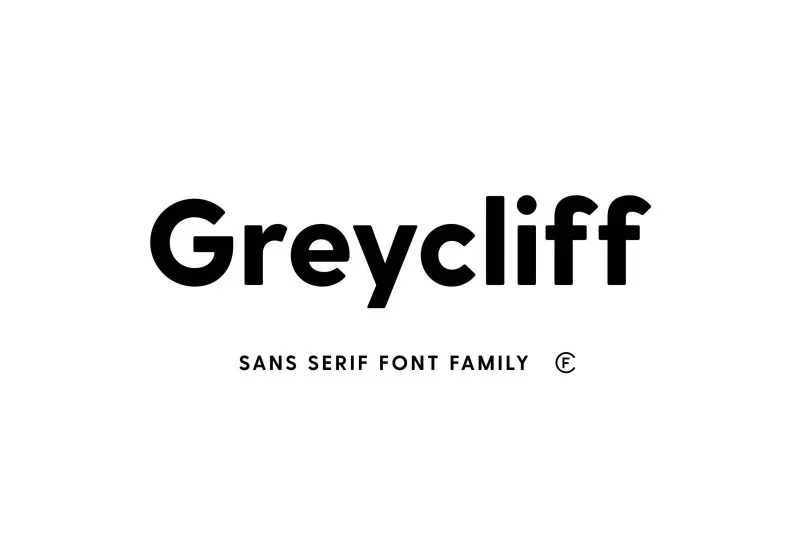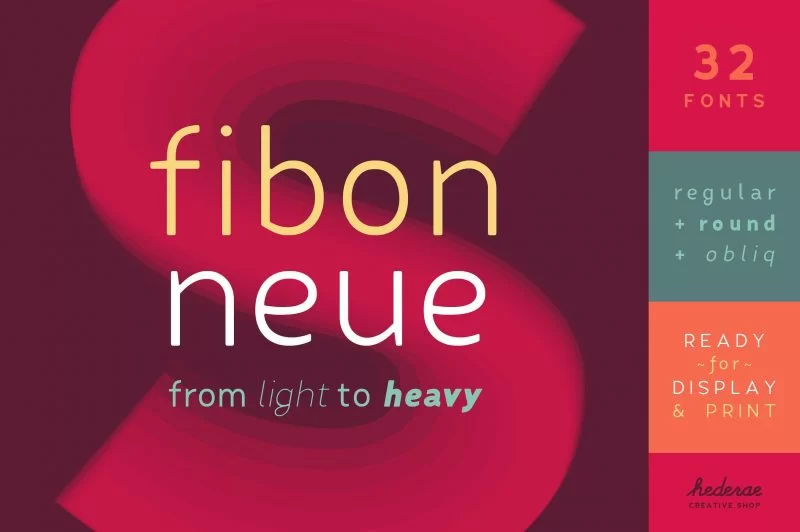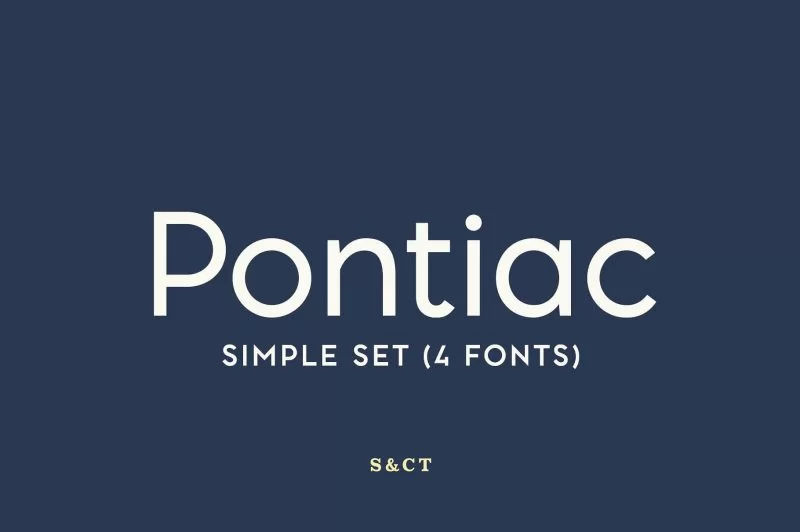
50 أفضل الخطوط للسيرة الذاتية
نشرت: 2022-06-25أفضل الخطوط على الإنترنت للسير الذاتية الإبداعية. فيما يلي قائمة شاملة بأفضل الخطوط للسيرة الذاتية لإحداث تأثير فوري.
هناك المئات من الأشياء التي يجب أن تترك السيرة الذاتية المثالية انطباعًا دائمًا ؛ الخط هو أحد أهم الخطوط على الإطلاق.
قد يكون لديك ألف خط للاختيار من بينها لإنشاء سيرتك الذاتية المثالية. ولكن لن تساعدك كل الخطوط في إنجاحها.
فيما يلي بعض من أفضل الخطوط سريعة الاستجابة التي تم إنشاؤها خصيصًا لهذا الغرض.
كاليبري
لا شك أن Calibri بتصميمها المستدير بمهارة هو أحد أفضل الخطوط لعمل السيرة الذاتية. له مظهر احترافي مع ميزات حديثة مقارنة بالخطوط الأخرى المتوفرة اليوم.
إنه الخط الافتراضي في PowerPoint و Excel و Word والعديد من المنصات البارزة الأخرى.
ستريما
هندسي بلا رقيق هو مثال نموذجي على بساطتها ووضوحها. يوفر دعمًا واسعًا للغة وميزات طباعة احترافية بالكامل.
هيلفيتيكا
إنه محرف يستخدم على نطاق واسع لأغراض السيرة الذاتية. بفضل تصميمها الواقعي ، تبرز Helvetica بين المحارف الأخرى.
تتضمن بعض الميزات البارزة للمحرف ارتفاع x عاليًا ، ويتم إنهاء الحدود على خطوط أفقية ورأسية ، وهناك ازدحام بين الأحرف حيث لا توجد مساحة كافية تؤدي إلى المظهر المضغوط.
كاريج
إنه محرف رائع يمكن استخدامه لأغراض عديدة. يتوفر أيضًا إصدار احترافي مع ميزات متقدمة.
تاهوما
إنه خط قياسي يوفر نظرة احترافية للسيرة الذاتية.
إنها تشبه إلى حد كبير Verdana ، تتميز Tahoma بعدادات صغيرة وأحرف أضيق مع مساحة صغيرة بينها ومجموعة أحرف Unicode كاملة.
كما أنها تستخدم على نطاق واسع في العديد من المنشورات الفنية.
فيردانا
Verdana مناسبة جدًا لعمل السير الذاتية بميزاتها المذهلة. إنه يظهر تشابهًا مع محرف إنساني بلا سيريف Frutiger.
تم إنشاؤه ليكون قابلاً للقراءة حتى في الأحجام الصغيرة على الشاشات منخفضة الدقة. تتضمن بعض ميزاته ارتفاع x كبير ، ونسب أوسع ، واحتقان أقل بين الأحرف على عكس الخطوط الأخرى مثل Helvetica.
نوتو
يوفر إمكانية قراءة رائعة عبر الإنترنت مع حوالي 93 نصًا مختلفًا للغة للاختيار من بينها.
إنه متوفر في إصدارات serif بالإضافة إلى إصدارات sans-serif مع ما يقرب من 600 لغة. إنه خط موصى به للغاية لاستئناف ra.
جورجيا
إذا كنت تبحث عن خطوط استثنائية للاستئناف ، ففكر في هذا الخط متعدد الاستخدامات جورجيا. إنه مستوحى من التصاميم الإسكتلندية الرومانية في أواخر القرن التاسع عشر.
يتضمن امتداد الخط المسمى Georgia Pro ميزات مثل الأوزان الإضافية ، وتصميمات الأحرف الصغيرة المتخصصة ، ومجموعة الأحرف الممتدة ، والأشكال المبطنّة ، إلخ.
Trebuchet MS
هذا محرف جميل مصمم لشركة Microsoft Corporation والذي سوف يلبي جميع متطلبات الخط ليتم عرضه في السيرة الذاتية.
Trebuchet هو أحد أشهر خطوط النص الأساسي التي تظهر على صفحات الويب. تتضمن بعض ميزاته الرائعة ذيولًا مختصرة من الأحرف الصغيرة "e" والأرقام "6" و "9" ، والذيل الهجين المفتوح والملفوف للحرف الصغير "g" ، وغير ذلك الكثير.
القرن القوطية
إنه محرف مصمم بأسلوب هندسي. تتأثر ميزاته بشكل كبير بالخط فوتورا ولها تصميم هندسي خالص يعتمد على أشكال مثل الدائرة. ميدان.
تتميز بأسلوب وجسم احترافي مما يجعلها خيارًا مناسبًا لسيرة ذاتية. التباعد الافتراضي بين الأحرف ضيق جدًا مما يمنحه تصميمًا فريدًا.
جيل سانس
Gill Sans عبارة عن محرف مذهل يركز بشكل صارم على إمكانية القراءة ويضيف أسلوبًا عصريًا أنيقًا إلى الكتابة.
إنه خط بسيط حيث تستند الأحرف الكبيرة على الأحرف الكبيرة الرومانية الموجودة في عمود تراجان ويظهر التباين في العرض.
لاتو
إنه محرف sans-serif يغطي الأبجديات اللاتينية بالإضافة إلى السيريلية واليونانية و IPA. يحمل سجلاً لكونه أكثر خطوط الويب استخدامًا بعد Robota و Open Sans.
يعتبر Lato مثاليًا لإنشاء سيرة ذاتية ويتميز بالعديد من الميزات الرائعة.
تايمز نيو رومان
يتم تعريفه على أنه محرف Serif تم إنشاؤه لتحقيق الوضوح في نصوص الجسم. على الرغم من استخدام Times New Roman بشكل شائع في الكتاب والطباعة العامة ، إلا أنه مناسب أيضًا لصنع السيرة الذاتية.
لاتينا
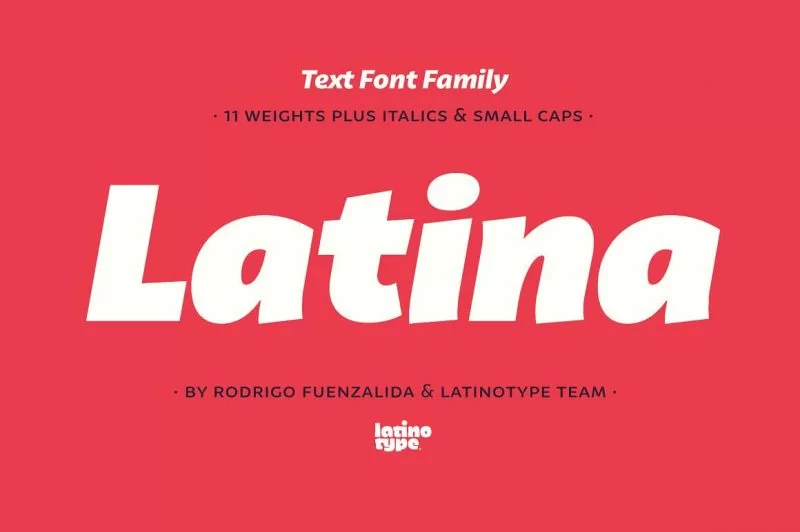
إنه محرف إنساني مناسب للاستخدام في النص المستمر. يدعم 219 لغة ومجموعة متنوعة من الأرقام.
كامبريا
خط Serif آخر مناسب للشاشة منخفضة الدقة ، إنه خط مثالي لعرضه في السيرة الذاتية.
في هذا الخط ، تكون الخطوط الرفيعة المائلة والعمودية أقوى ويتم التأكيد عليها بشكل أساسي بالخط المائل حيث يتم عرض الأحرف الصغيرة بأسلوب محض.
أنتيكوا
إنه محرف يشبه الكتابة اليدوية أو الخط الموجود خلال القرنين الخامس عشر والسادس عشر .
إنه أحد أفضل الخطوط التي يجب مراعاتها لعمل السير الذاتية. يمكن قراءتها بسهولة على الشاشات والشاشات الصغيرة.
ديدوت
ديدوت هو خط أنيق من شأنه أن يضيف أناقة إلى سيرتك الذاتية. تم تصميمه قبل الثورة الفرنسية ويستخدم على نطاق واسع بين المحترفين.
بلا هزلية
إنه محرف sans-serif مناسب فقط للاستئناف والاستخدامات الاحترافية الأخرى. إنه يتميز بنص غير رسمي ولكنه غير متصل مستوحى من الكتب المصورة.
تم استخدامه على نطاق واسع.
هدسون نيويورك
هذا خط من نوع العرض يوفر لك طباعة جريئة واحترافية. تم تكييف ميزاته بشكل كبير من Roper Font وتشمل الإصدارات العادية والصحفية.
إنه يمتلك مظهرًا أصيلًا ومجموعة حديثة من مجموعات الشخصيات.
مانهاتن
إنه محرف بسيط يتميز بخطوط أنيقة ورقيقة رفيعة ويبدو مثالياً في السيرة الذاتية. يقترن جيدًا مع الخطوط الأخرى ويساعد في أي مشروع تعمل عليه.
يتكون من رموز رياضية تجعله أحد المحارف القليلة التي تتميز بالتنضيد الرياضي.
الفجر
إنه محرف مفعم بالحيوية مستوحى من Aurora ويأتي مع العديد من الأحرف والأحرف المركبة.
ألتا
إنه محرف sans-serif يتضمن تعليقًا عاديًا وخفيفًا وشرحًا. إنه إنساني يعتمد على شخصيات خط Optima.
من المحتمل أن تكون السيرة الذاتية هي المستند الأول الذي تشاركه مع صاحب العمل ، ومن ثم عليك توفير مزيد من العناية أثناء اختيار الخطوط لنفسها لأنها مهمة.